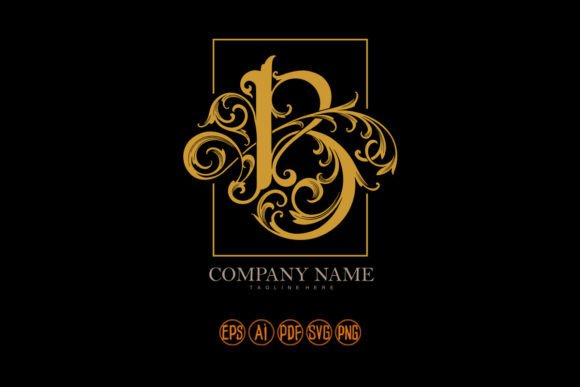
Sophisticated Elegant B Monogram Letter
適切なデザイン要素を見つけるのは難しい場合がありますが、Sophisticated Elegant B Monogram Letterは作品を即座に引き立てる優れたコレクションを提供します。
精密に作られたSophisticated Elegant B Monogram Letterは、クリーンなベクター、滑らかなタイポグラフィ、そして安心のための商用ライセンスを提供します。